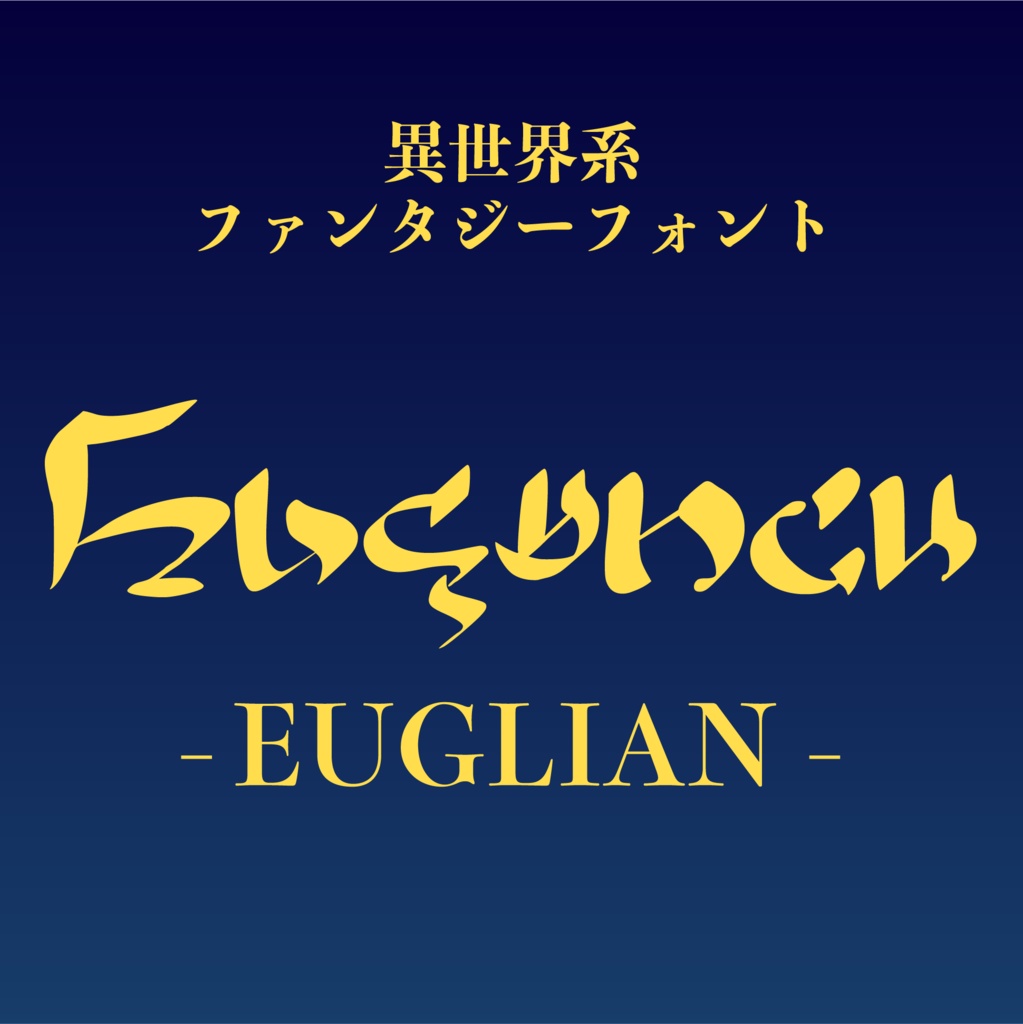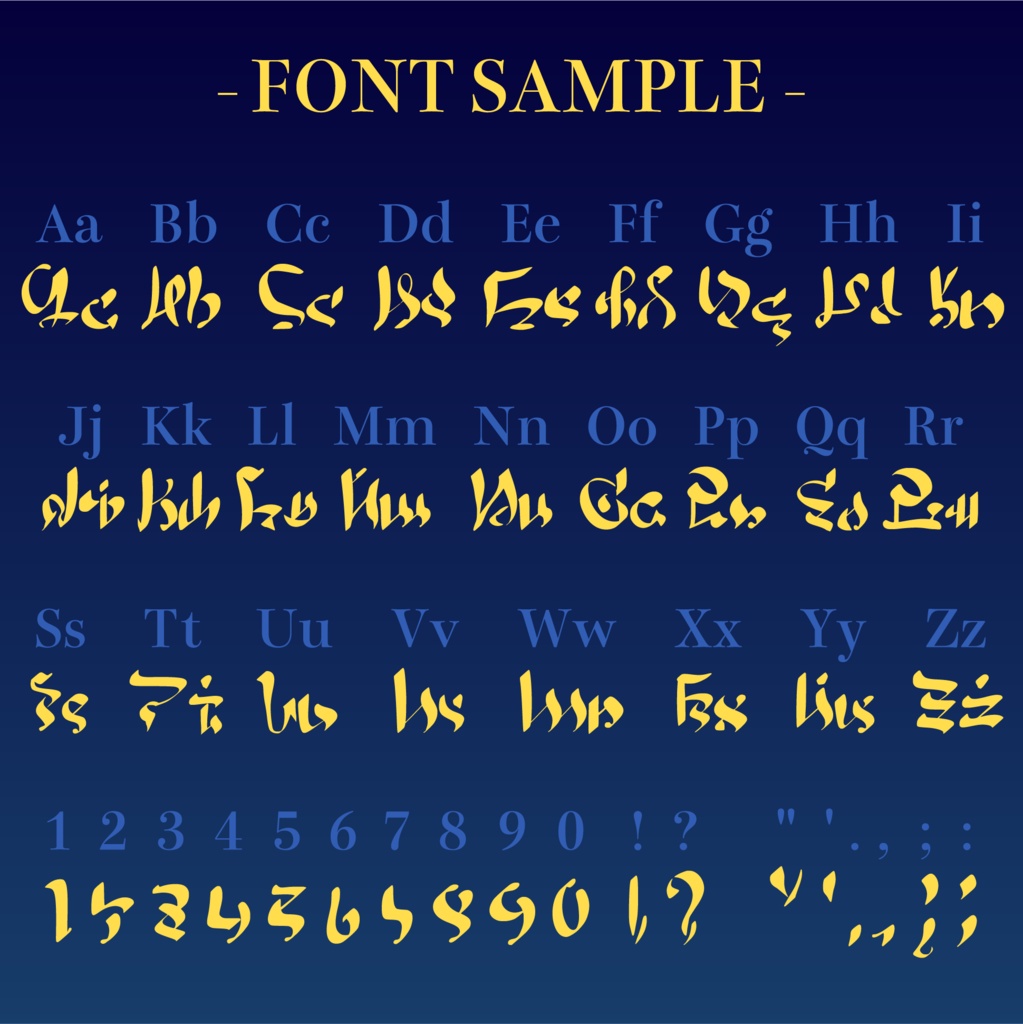
Fantasy Font | Euglian
ファンタジー系のTRPG等で使うことを想定して制作したフォントです。 魔法や魔術が台頭していた時代の文明の文字を意識して制作しました。魔法陣などに使うと結構映えると思います。 ---- 「Fantasy Font シリーズ 全6書体全部入りセット」をご購入すると格安で入手できてお得です。ぜひこちらをどうぞ! https://soya-workshop.booth.pm/items/4766747